Le lettere del logo sono una versione stilizzata della firma di Walt Disney. È il logo aziendale dal 1956, e non è mai stato pubblicato come carattere tipografico: non esiste nessun file ufficiale da installare. Il font che tutti scaricano al suo posto è Waltograph, disegnato da Justin Callaghan per ricalcare il logotipo. Esiste in due varianti: Waltograph 42, con maiuscole e minuscole più qualche legatura e lettera alternativa, e Waltograph UI, una versione unicase fatta per restare leggibile in piccolo e sullo schermo. Entrambe sono gratuite per uso personale.
Come creare un testo Disney
Passo 1. Scrivi il nome
Apri il generatore e sostituisci il testo di esempio con il tuo: il nome di un bambino, il titolo di una festa, un cognome per la maglietta di un viaggio. Le lettere si ridisegnano mentre scrivi. Tienilo in minuscolo con l'iniziale maiuscola: lo stile firma è un corsivo, e una parola tutta in maiuscolo perde la grande D ad anello che la fa riconoscere come Disney.
Passo 2. Scegli uno stile
Il classico è il corsivo firma bianco su una sfumatura blu reale. La scheda Stili permette di cambiare separatamente riempimento, contorno e ombra, così tieni la forma delle lettere e porti i colori altrove: oro su blu navy per un matrimonio, rosa per una festa da principessa.
Passo 3. Scegli il formato
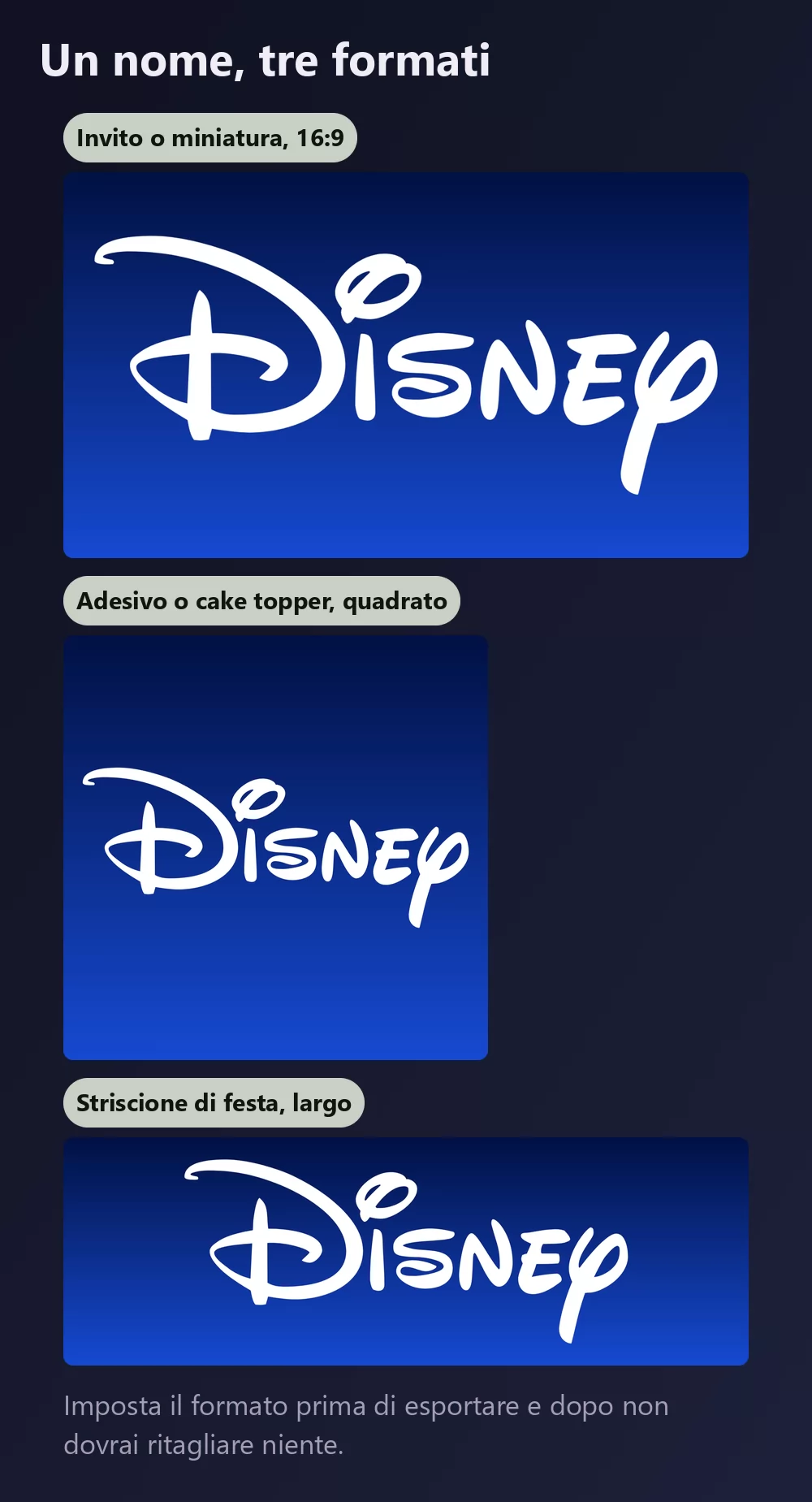
Imposta il formato prima di esportare e dopo non dovrai ritagliare niente. Un 16:9 per un invito o una miniatura video, un quadrato per un adesivo o un cake topper, una striscia larga per uno striscione lungo una parete.
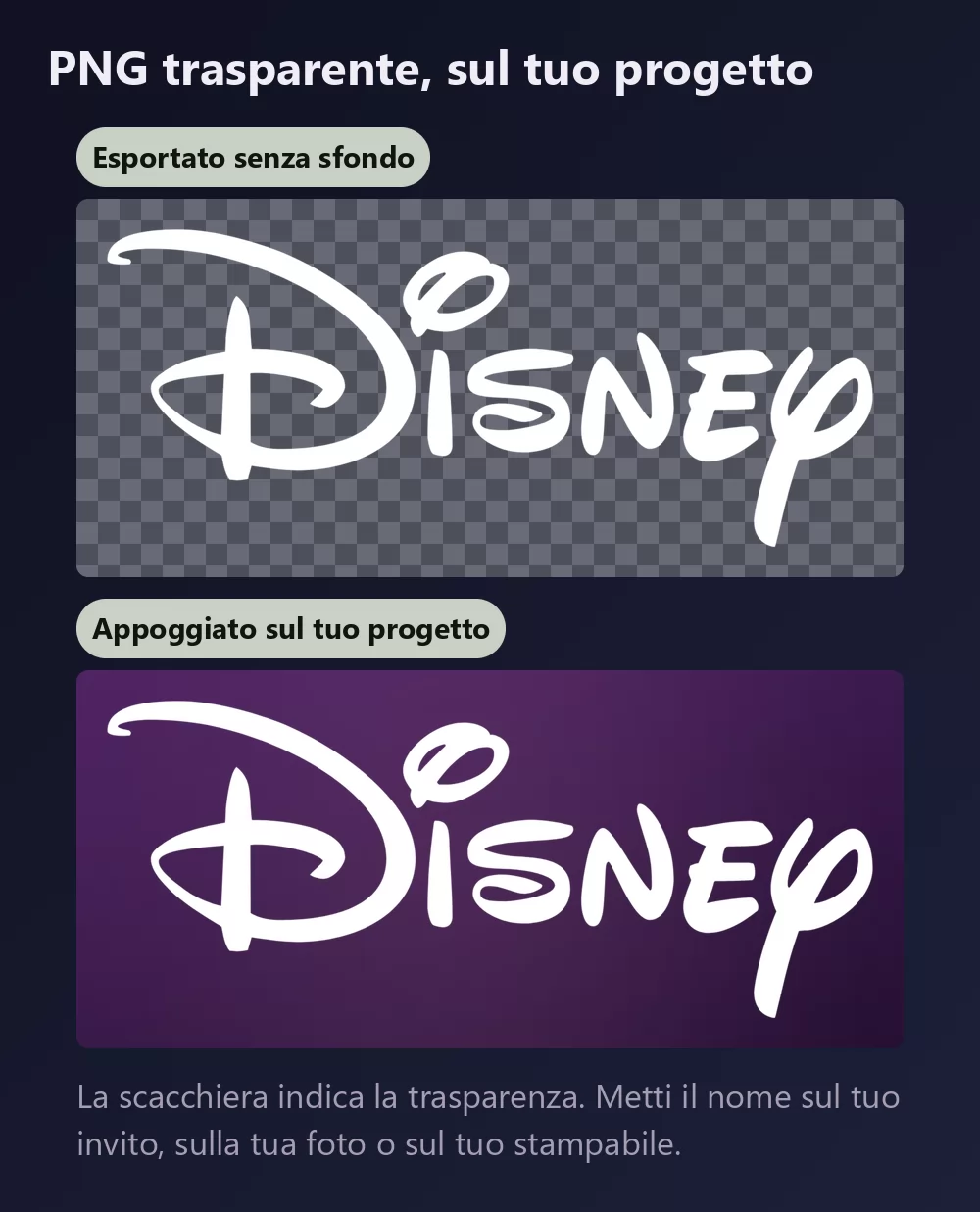
I nomi lunghi riempiono subito la larghezza
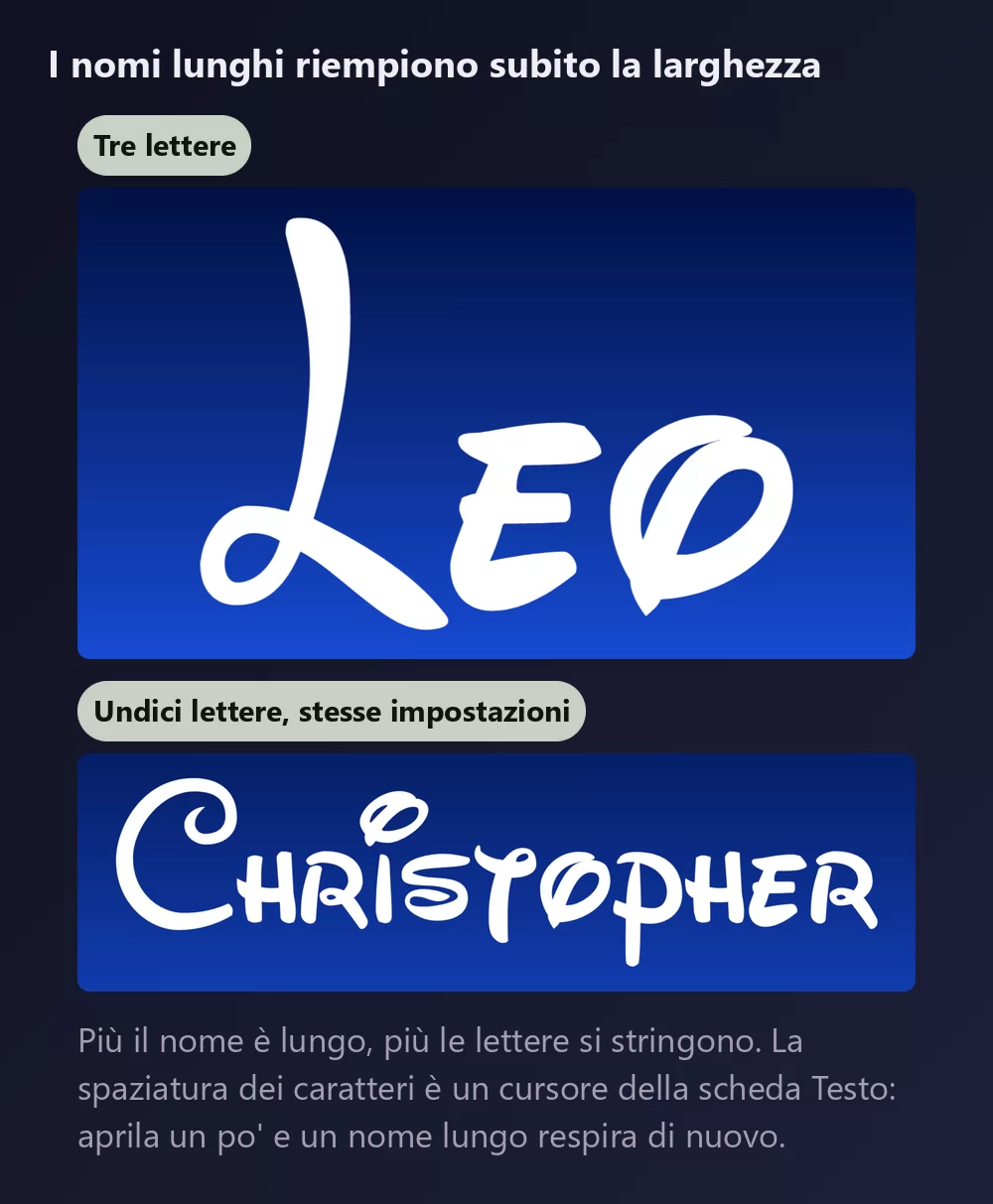
Più lettere ci sono, più si stringono. La spaziatura dei caratteri è un cursore della scheda Testo: aprila un po' e un nome lungo smette di sembrare schiacciato. La stessa scheda ha zoom, interlinea, curva e rotazione.
Lo stile firma o lo stile Topolino
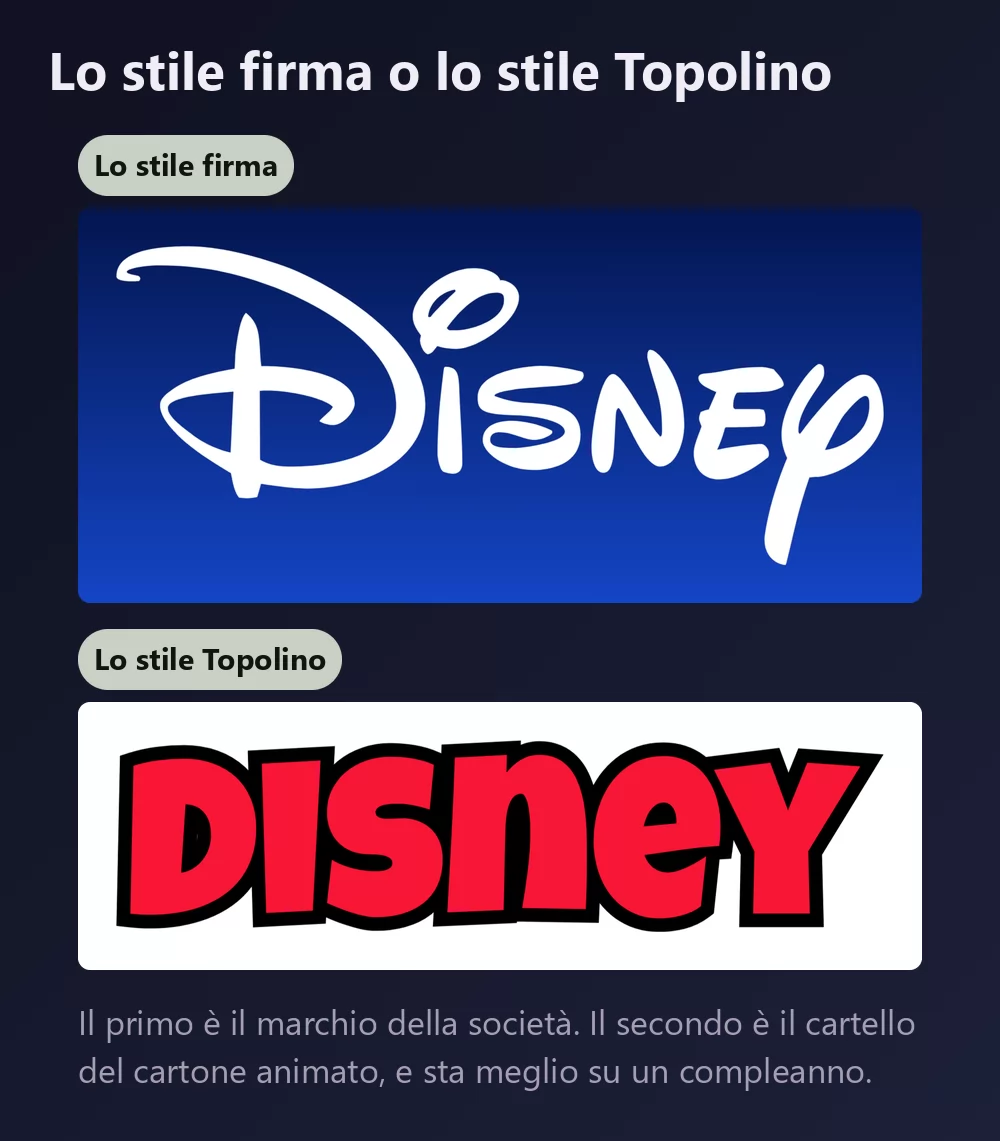
Lo stile firma è il marchio della società: un corsivo fluido con la grande D ad anello, bianco su blu. È quello che quasi tutti hanno in mente quando dicono "il font Disney".
Lo stile Topolino è il cartello dei cartoni animati: maiuscole rosse spesse con contorno nero, le lettere dei cortometraggi di Topolino. Non porta nessun marchio aziendale, si legge dall'altra parte della stanza, e per un primo compleanno di solito funziona meglio della firma. Il generatore di font Topolino lo ha tra le impostazioni.
Quale font, se vuoi installarne uno
Il logo in sé non è un font. È un lettering fatto su misura, quindi qualsiasi file chiamato "font Disney" è la ricostruzione di qualcuno.
Mouse Memoirs, di Astigmatic, è quello da scegliere quando la licenza deve essere pulita. È su Google Fonts sotto Open Font License dal 2012, il che lo rende libero per uso commerciale. Non è una copia della firma: è un sans alto, letterato a mano nello spirito dei primi cartoni, e si abbina bene allo stile firma su un poster o un menu.
Font Disney per film e personaggio
Il logo della società è una cosa. Ogni film ha il proprio lettering del titolo, e la maggior parte dei risultati di ricerca per "font Disney" sono in realtà elenchi di quelli. Lo stesso generatore ha uno stile per quasi tutti, ciascuno sulla propria pagina:
- font Topolino : maiuscole rosse spesse con contorno nero
- font Minnie : pois rosa e un fiocco su ogni lettera
- font Frozen : maiuscole azzurro ghiaccio con la brina sui bordi
- font Toy Story : lettere gialle con contorno blu su un blocco rosso, e abbiamo una guida completa a Toy Story
Devo scrivere in maiuscolo? No. La firma è un corsivo, e il suo carattere viene dalla grande D ad anello e dalle minuscole. In maiuscolo si perde.